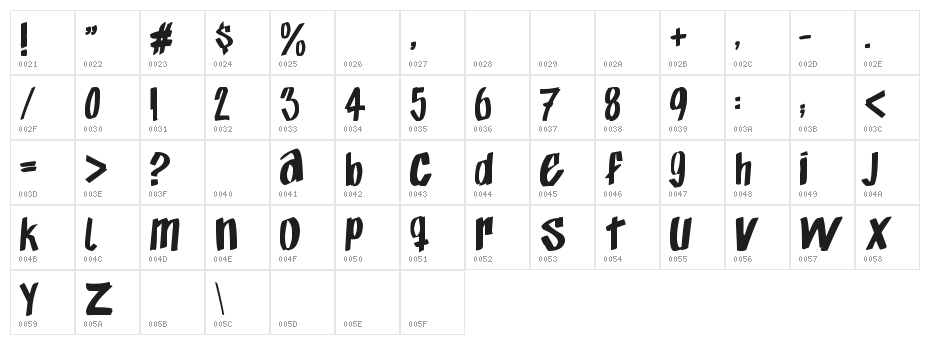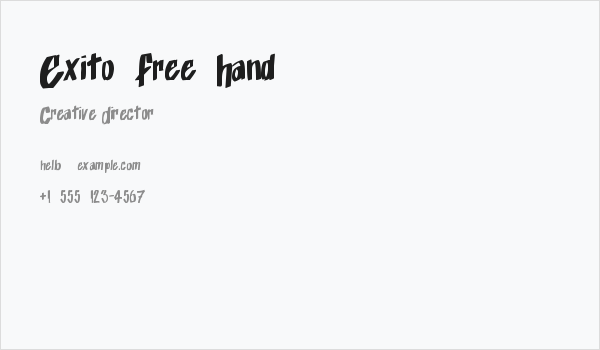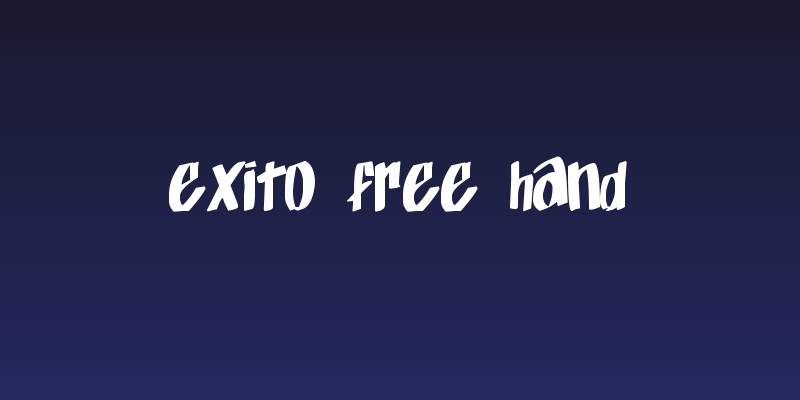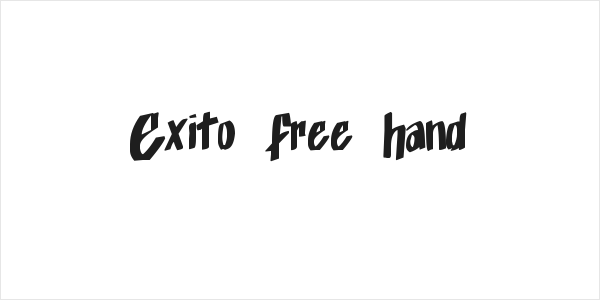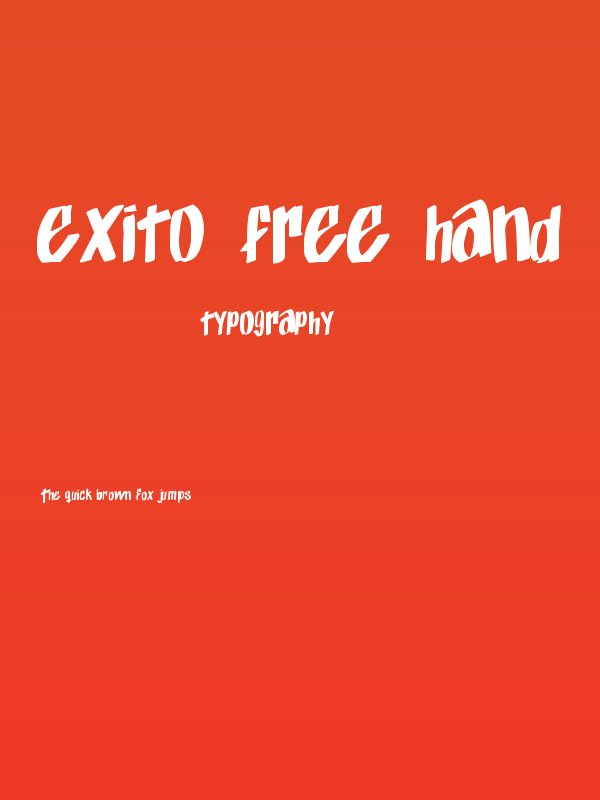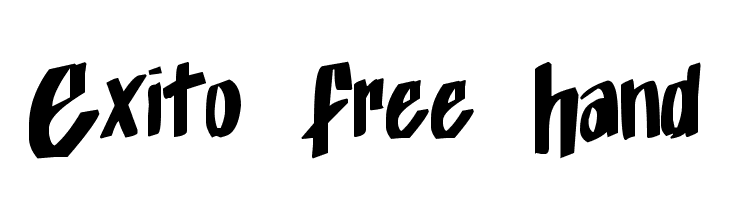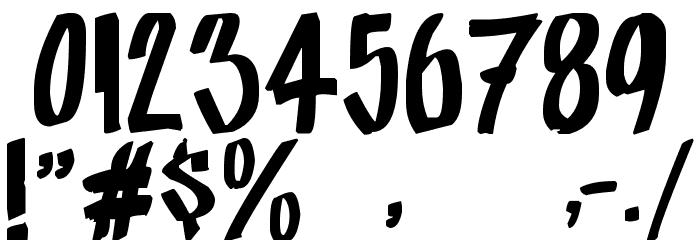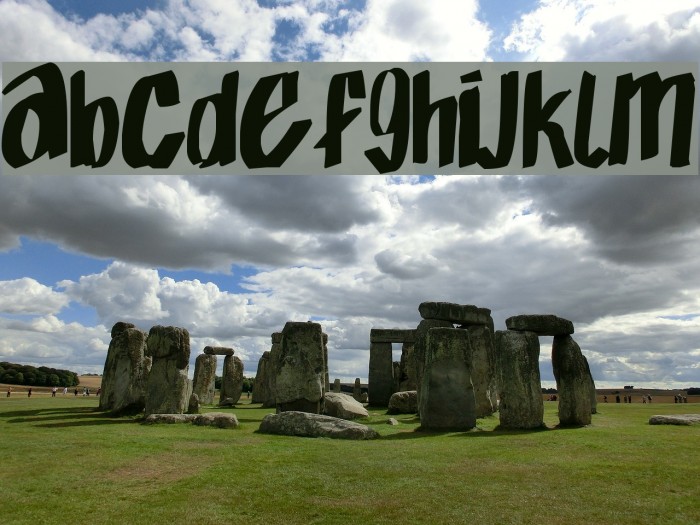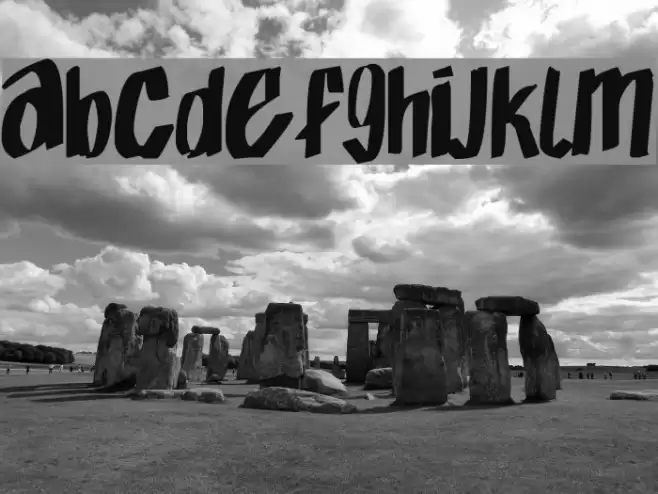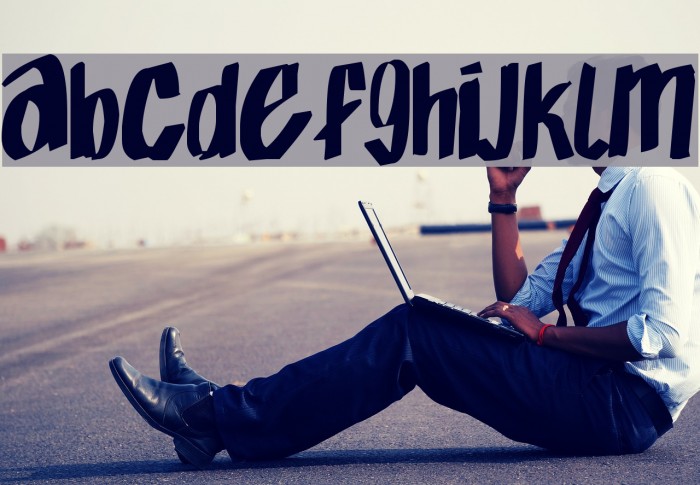
Exito_Free_Hand Font
| Projetos propostos | Ideal for creative projects such as posters, invitations, branding, and social media graphics where a personal and artistic touch is desired. |